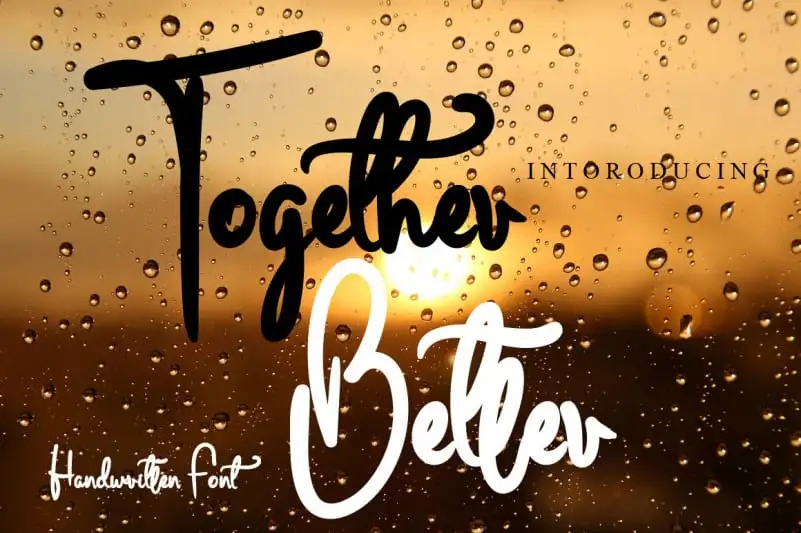
Together Better Script Font – Download Grátis
A ‘Together Better Script Font’ é uma elegante cauda escrita a mão que se destaca pela sua textura suave e natural, parecendo fresca e despojada, como se tivesse sido traçada com um pincel de pintura ao ar livre. Esta fonte retrata um estilo único e espontâneo, perfeitamente adaptável a uma ampla variedade de projetos gráficos. Seja para marcar capas de livros, criar tags em redes sociais ou mesmo decorar mensagens de texto, essa font se destaca pela sua personalidade única e facilmente modificável. Descubra o deslumbrante potencial dessa fonte alegre e explore seus inúmeros estilos possíveis.